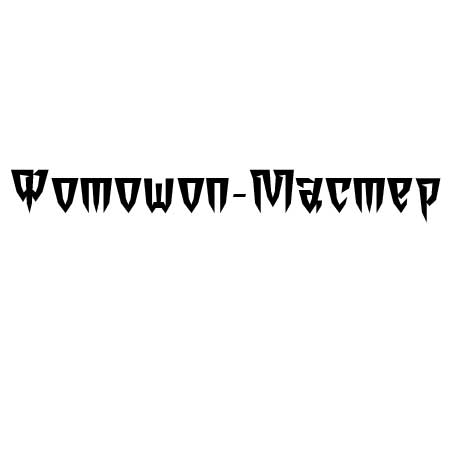
Этот шрифт в документе WORD требует для себя 10-кратную (даже больше) высоту строки.
Т.е. между предыдущей строкой (с другим шрифтом) и строкой с ЭТИМ шрифтом будет очень много свободного места
(поместилось бы с десяток других строк..) (((
Приблизительно вот так (точкой отмечена условно высота строки с надписью, сделанной при помощи "Шрифт - Оrden"):
Шрифт - Оrden
ЗЫ. В Фотошопе - всё нормально.
ХаХа, подойдёт для надписей Хелоуууиинаааа))) Суперский сайт)))
Жаль латиницу не держит) А так красивый шрифт )
оч оригинально!